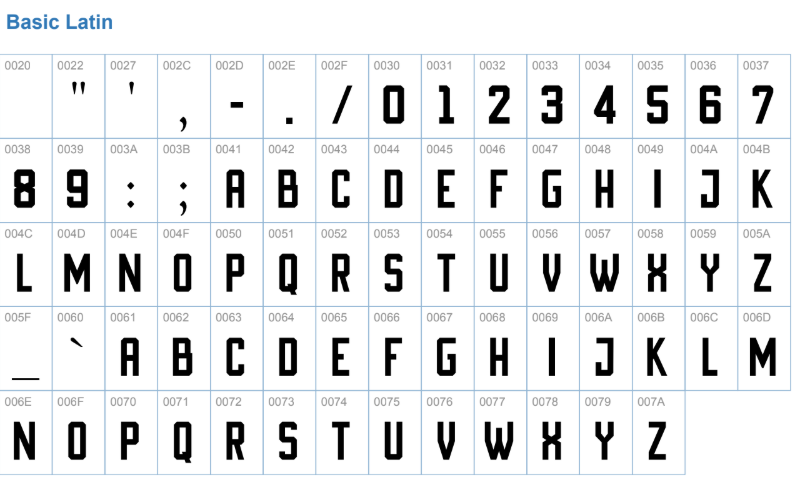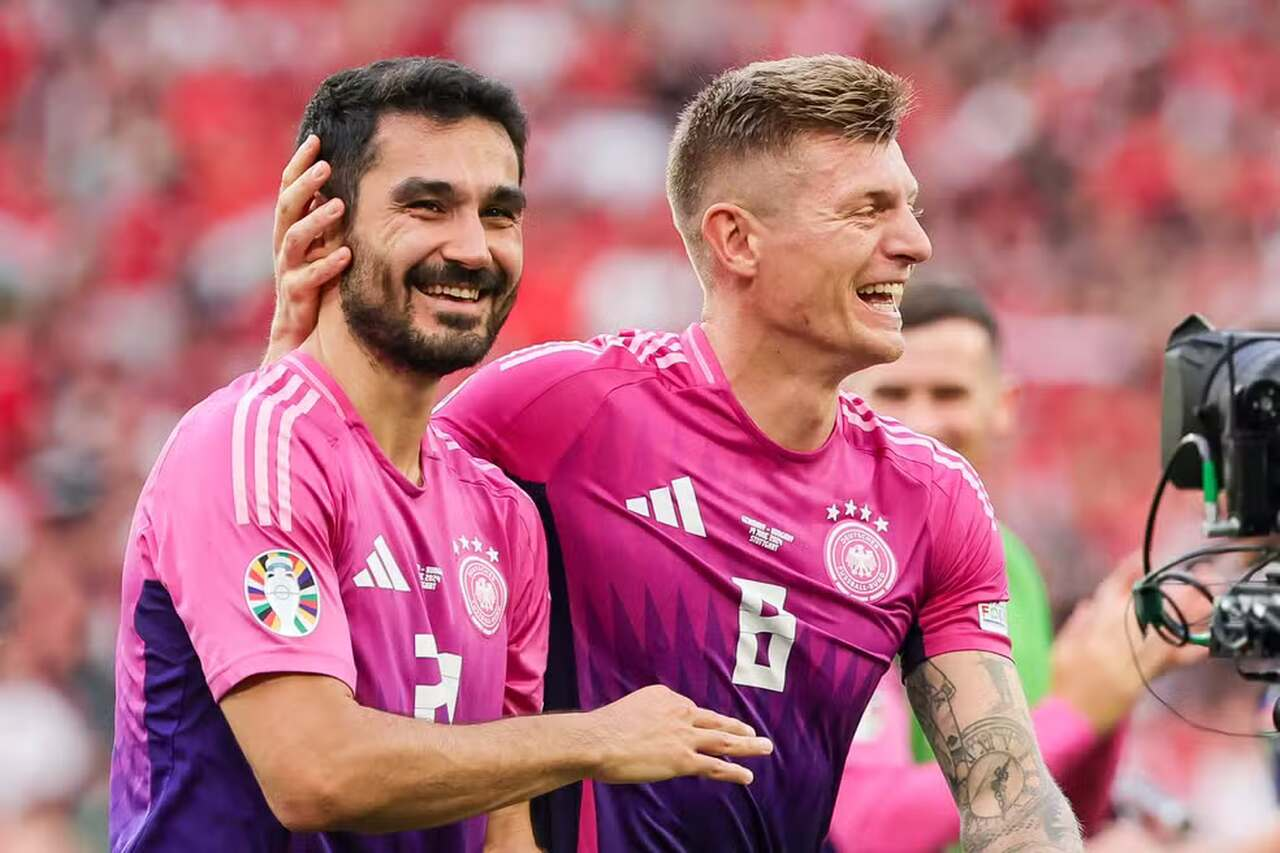
A seleção alemã entra em 2026 com um segundo uniforme que resgata o peso da tradição com um olhar firme para o futuro. A nova camisa reserva chega carregada de simbolismo, e a escolha tipográfica é parte central dessa entrega visual — um elemento que conecta o torcedor à essência da Mannschaft antes mesmo do apito inicial.
Designers, criadores de conteúdo e fãs já tratam a fonte oficial como item obrigatório da temporada. Seja para personalizar materiais ou para manter a coleção digital em dia, a tipografia do uniforme alternativo entrega personalidade e reforça o padrão gráfico da Federação Alemã de Futebol.
Estilo visual da tipografia
A fonte do segundo uniforme aposta em traços retos e bem definidos, com números que ganham presença sem pesar na composição. O desenho moderno mantém alta legibilidade tanto no estádio quanto nas transmissões em telas menores — um cuidado essencial para o futebol conectado de hoje.
A construção dos caracteres prioriza o impacto visual em movimento. As hastes firmes e o espaçamento generoso garantem leitura limpa em planos abertos e câmeras distantes.
Aplicação no uniforme
Home (titular): O uniforme principal mantém outra família tipográfica, preservando a identidade clássica.
Away (reserva): A fonte 2026 estreia com destaque na camisa visitante. Os números pretos aplicados sobre o tecido claro criam contraste imediato.
Third (terceiro uniforme): A terceira peça, quando lançada, deve seguir a mesma base tipográfica do away, unificando a comunicação visual alternativa.